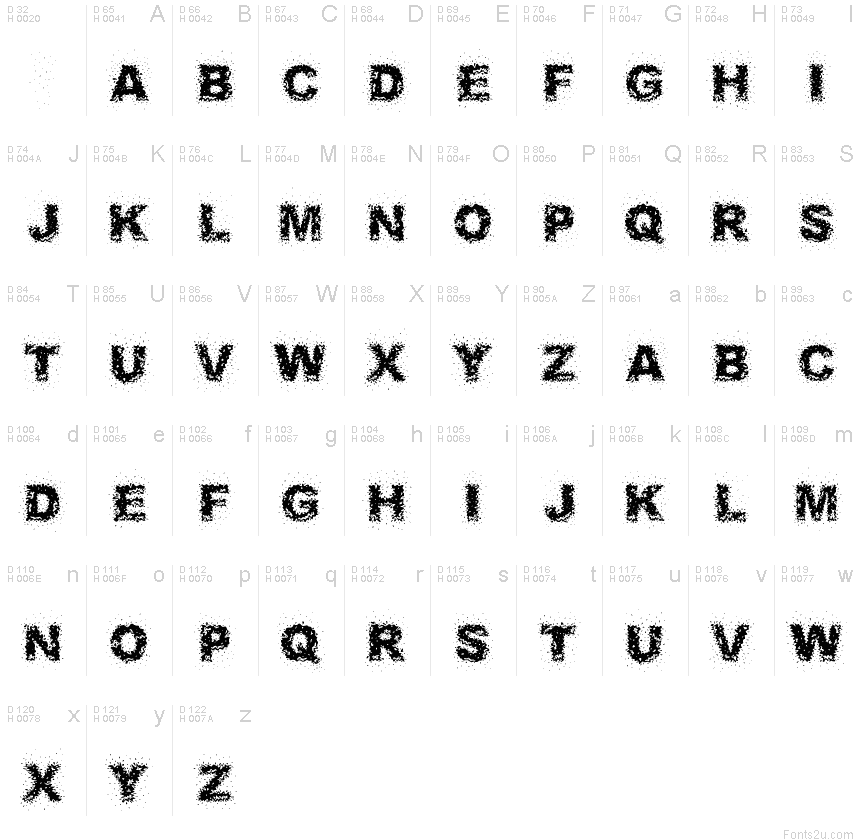
Fuzzed autorstwa Jamesa Shieldsa to darmowy, erodowany krój typu display, który wygląda, jakby wibrował od statycznych zakłóceń. Każda litera to masywny czarny kształt, otoczony ostrymi drobinkami i drżącymi konturami – sprawia wrażenie, jakby wyrywała się ze strony lub była zjadana przez cyfrowy szum. Tekstura jest ziarnista i pełna energii, a nie tylko brudna, dzięki czemu Twoje napisy zyskują głośną, elektryzującą obecność nawet na czystym, białym tle.
Ten darmowy font świetnie sprawdza się na plakatach horrorów, ulotkach muzyki glitch, zinach, tytułach gier, grafikach na Halloween i każdej pracy, która potrzebuje dzikiego, niestabilnego charakteru. Użycie Fuzzed w dużym rozmiarze pozwala w pełni wyeksponować te skwierczące detale, podczas gdy prosty krój bezszeryfowy w tekście głównym zapewni równowagę całego projektu.